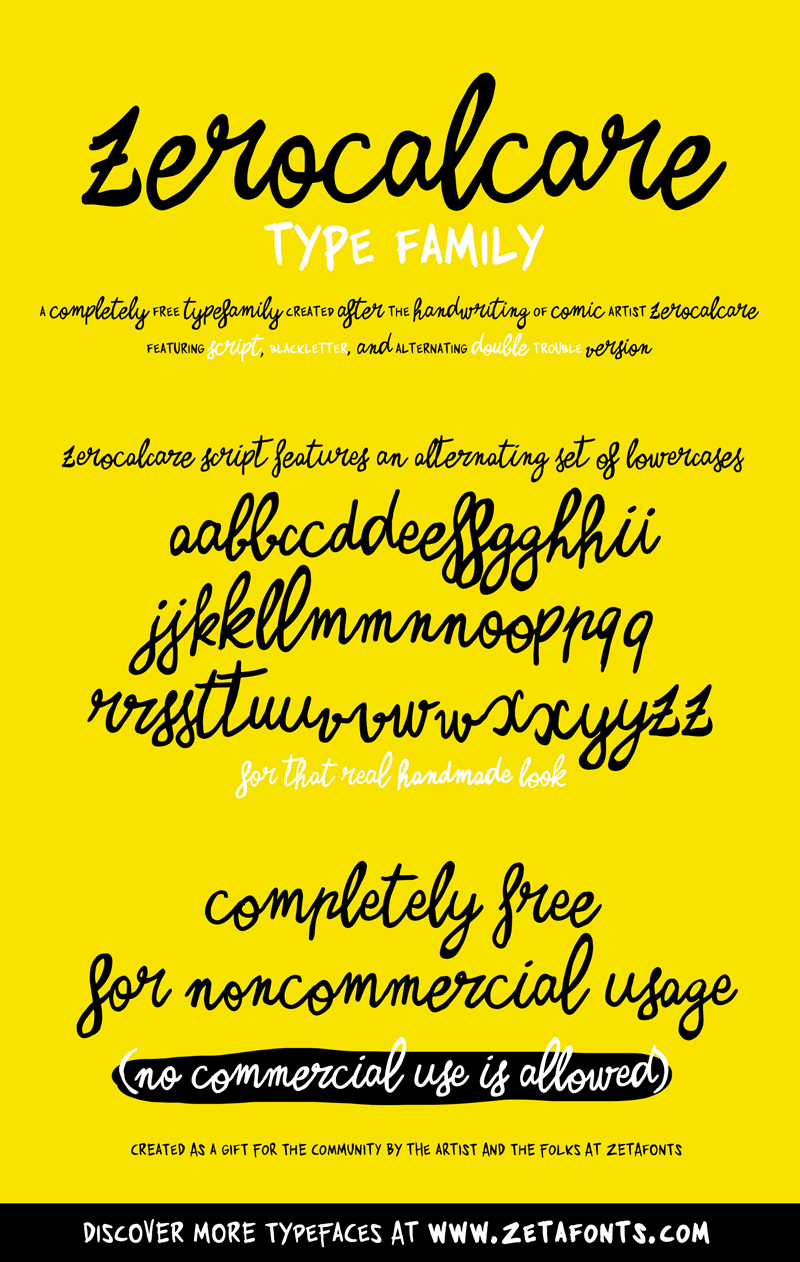
Zerocalcare Script Font – Fonte Grátis
Zerocalcare Script Font
A Zerocalcare Script Font é uma família de tipos criada para a identidade visual do Lucca Comics & Games Festival 2016. Ela se baseia na escrita digitalizada de um artista italiano de quadrinhos chamado Zerocalcare, reconhecendo e imitando a fluidez da sua própria arte manual. Esta fonte abraçada às características do desenho à mão livre oferece uma experiência visual única e emocionante para qualquer projeto de design gráfico. Com seu uso inteligente de caracteres abertos e substituições, ela permite que as letras se movam como se fossem escritas a mão real, criando um entrelaçamento fluido e autêntico. Para quem busca uma fonte elegante e única para seus projetos, não há melhor escolha do que experimentar a Zerocalcare Script Font da Zetafonts.